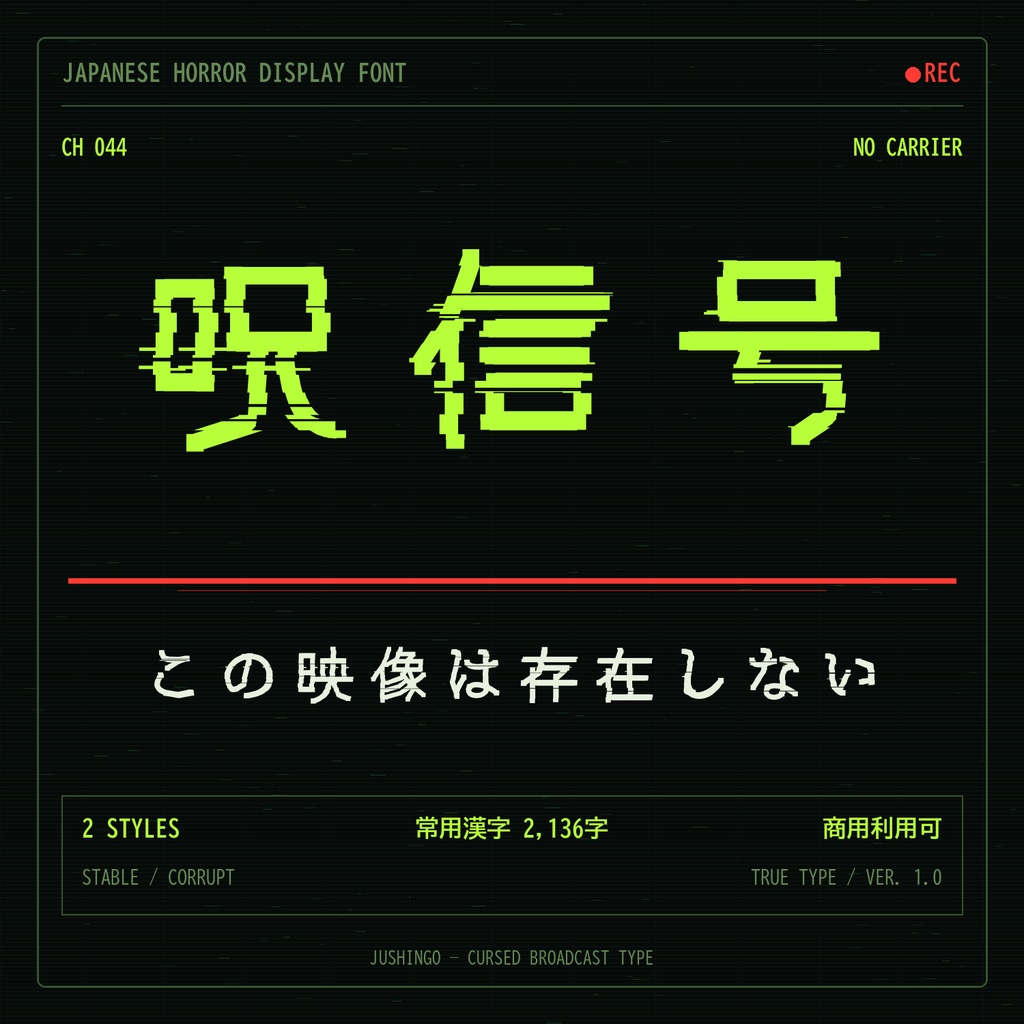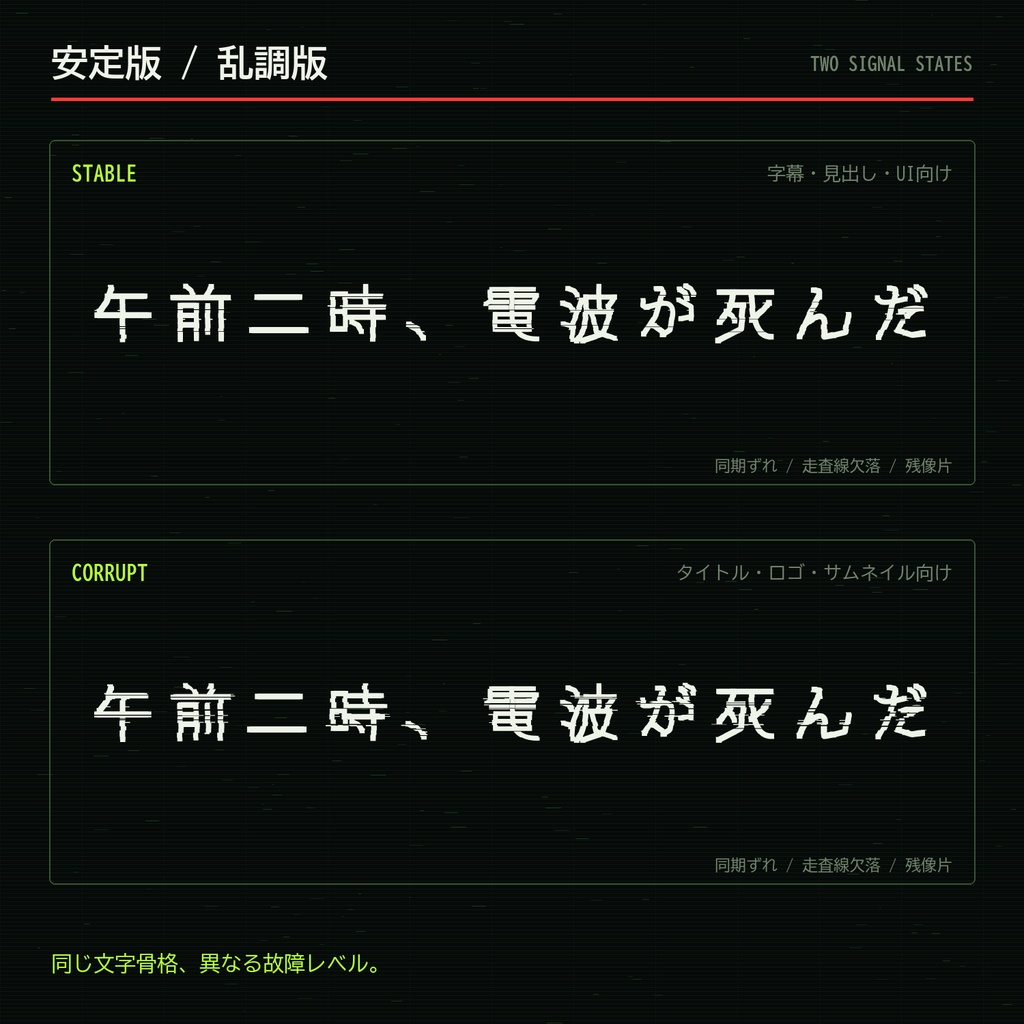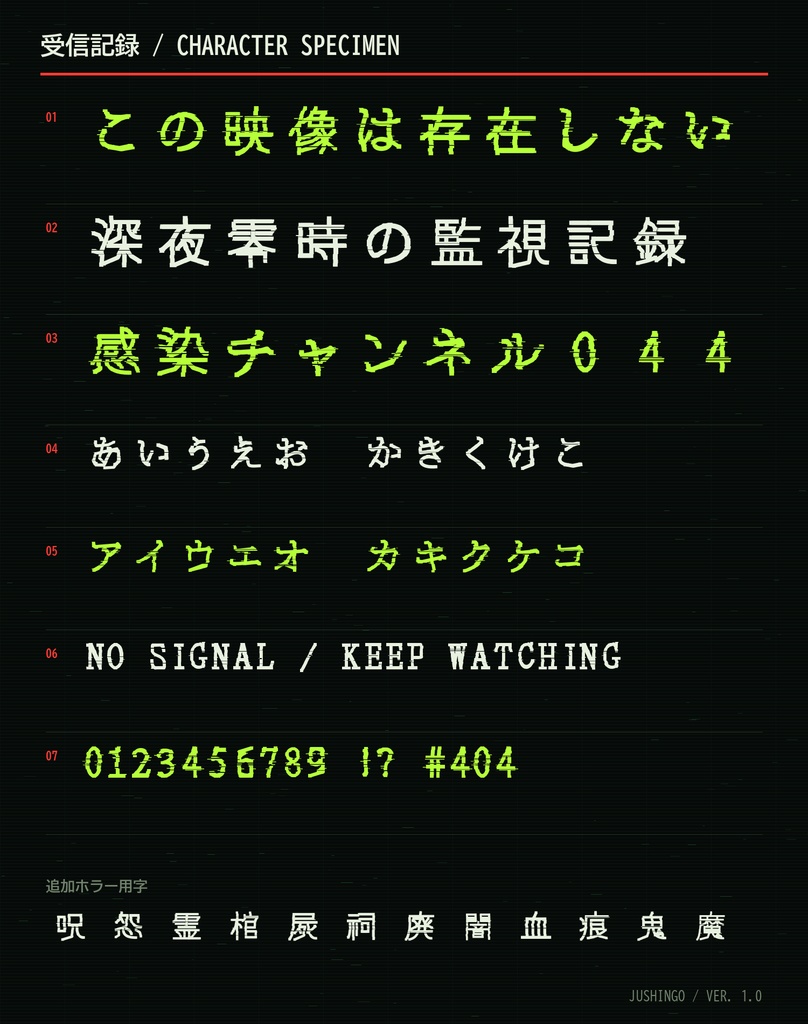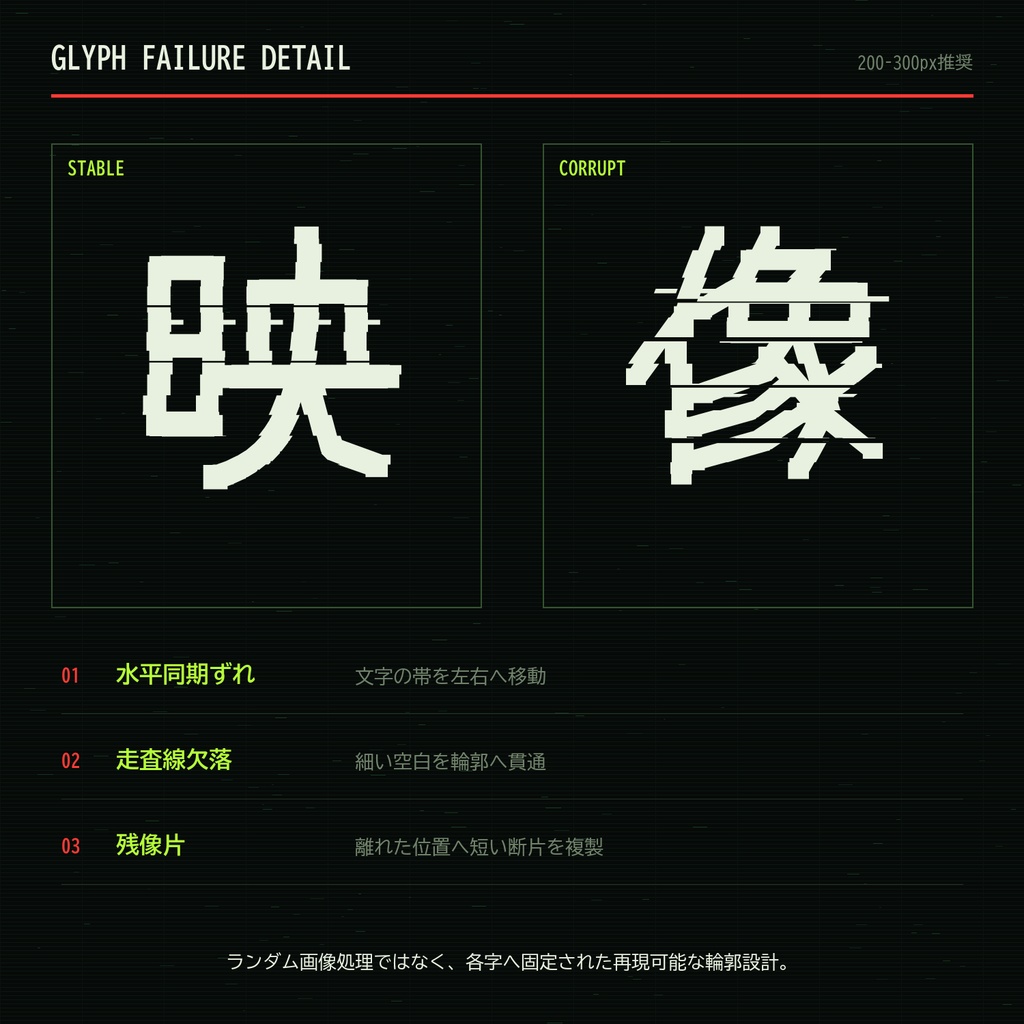
【呪信号】VHS・監視映像ホラー向け日本語フォント|常用漢字+2書体
【呪信号 / JUSHINGO】 読める。けれど、映像のどこかが壊れている。 『呪信号』は、横方向の同期ずれ・走査線欠落・残像片を字形そのものへ組み込んだ、日本語ホラーディスプレイフォントです。 ■ 特徴 ・全字を同じ「水平同期エラー」のルールで設計 ・安定版と乱調版の2書体を同梱 ・遠目では読め、近づくと走査線の切断と横ずれが見える ・ひらがな、カタカナ、英数字、常用漢字2,136字を収録 ・「呪・怨・霊・棺・屍・祠・廃・監視・映像・電波」などホラー/放送用字を追加 ・商用作品、ロゴ、動画、配信、ゲームへの使用可 ■ 2つの書体 ・JushinGo Stable:可読性優先。字幕、章見出し、UI向け ・JushinGo Corrupt:同期ずれを強化。タイトル、ロゴ、サムネイル向け ■ 向いている用途 VHSホラー、監視カメラ、呪われた放送、アナログホラー、TRPG、マーダーミステリー、ゲーム画面、配信サムネイル、動画テロップ、CDジャケット。 ■ 収録形式 TrueType(TTF)2種 / Windows・macOS ■ 推奨サイズ Stable:24px以上 Corrupt:48px以上 ■ 利用 個人・商用利用可。クレジット不要です。 フォントファイルそのものの再配布・共有・転売は禁止です。 詳細はZIP内の利用規約をご確認ください。 ※本書体はGlyphWiki由来のKAGEデータを独自アウトラインへ再構築しています。出所記録とGlyphWikiライセンスを同梱しています。